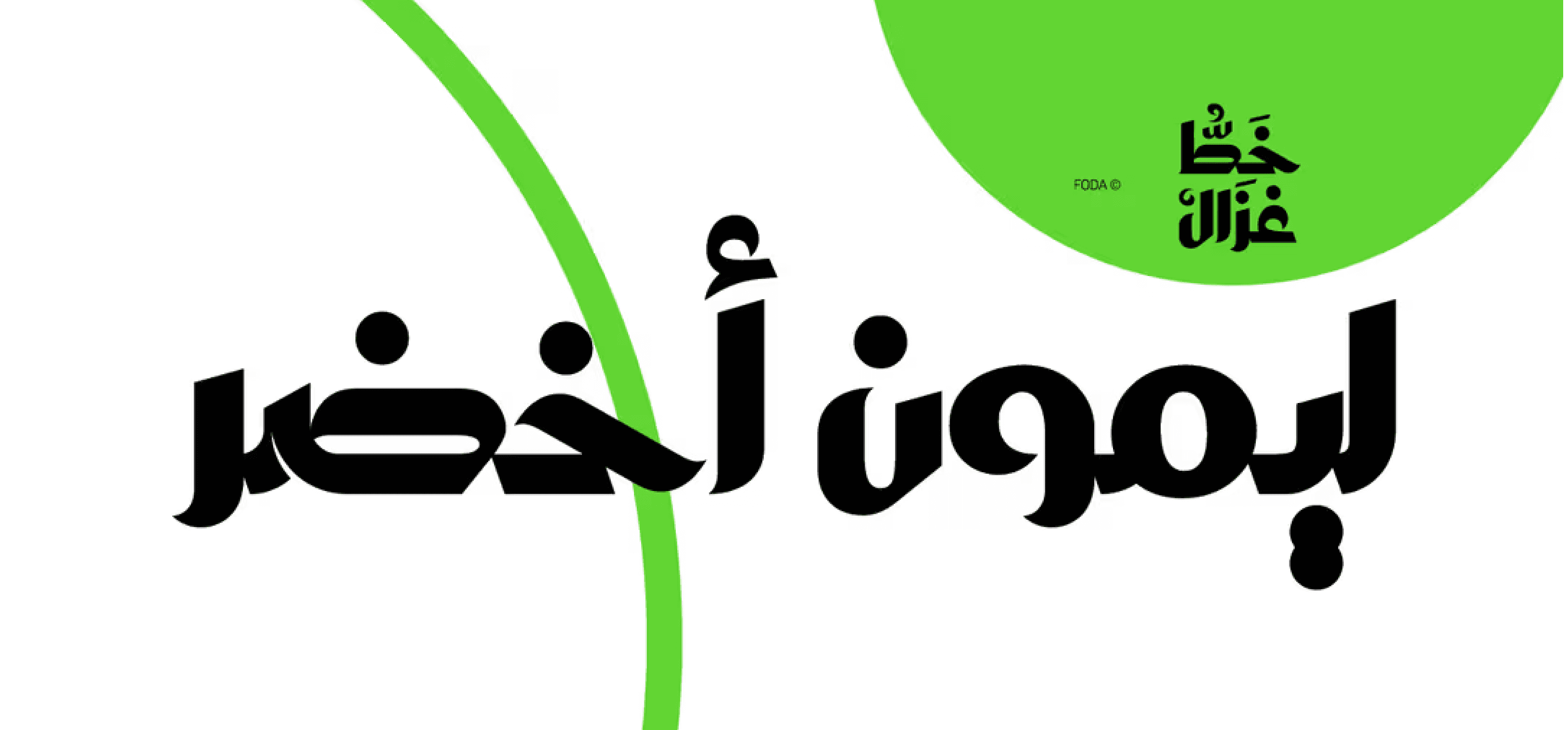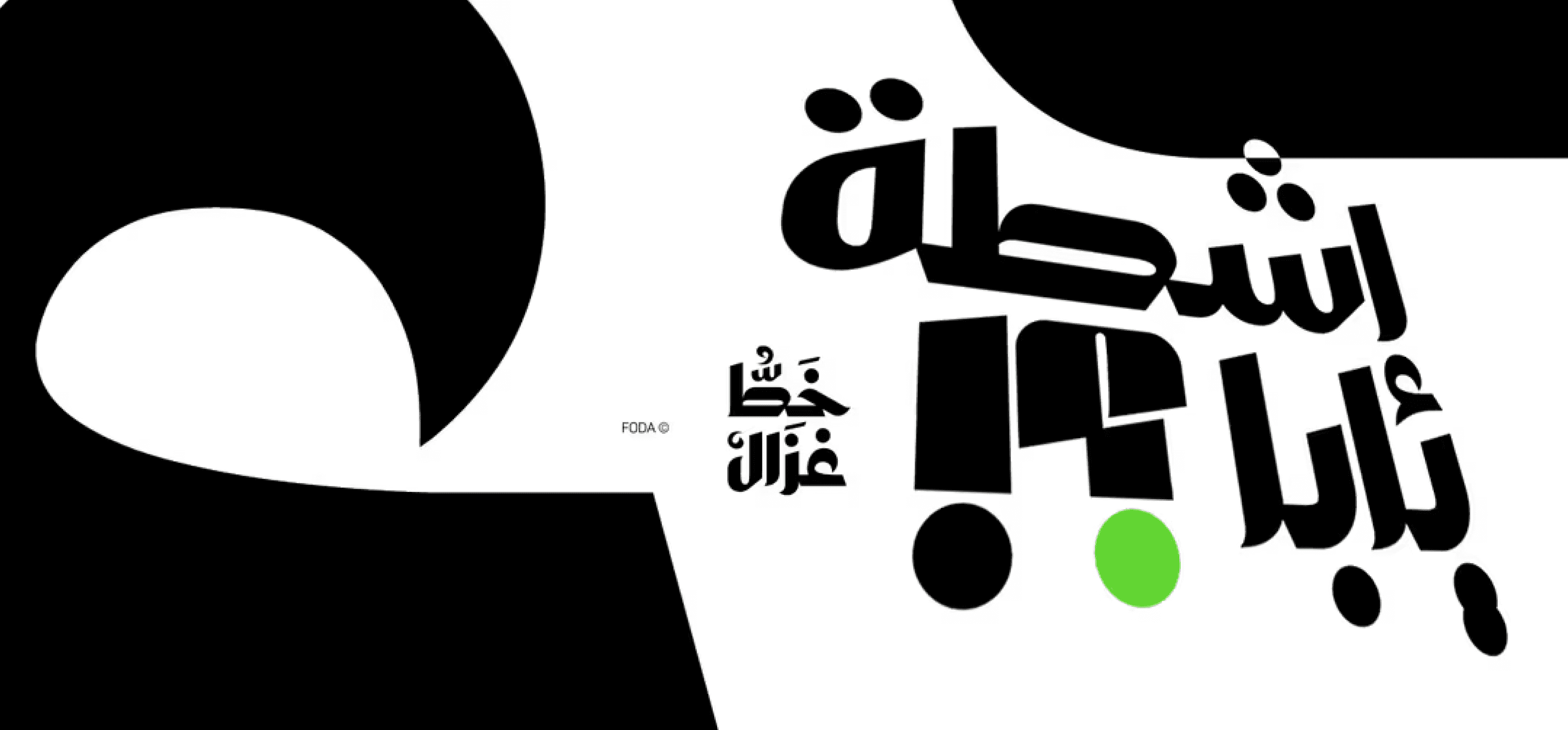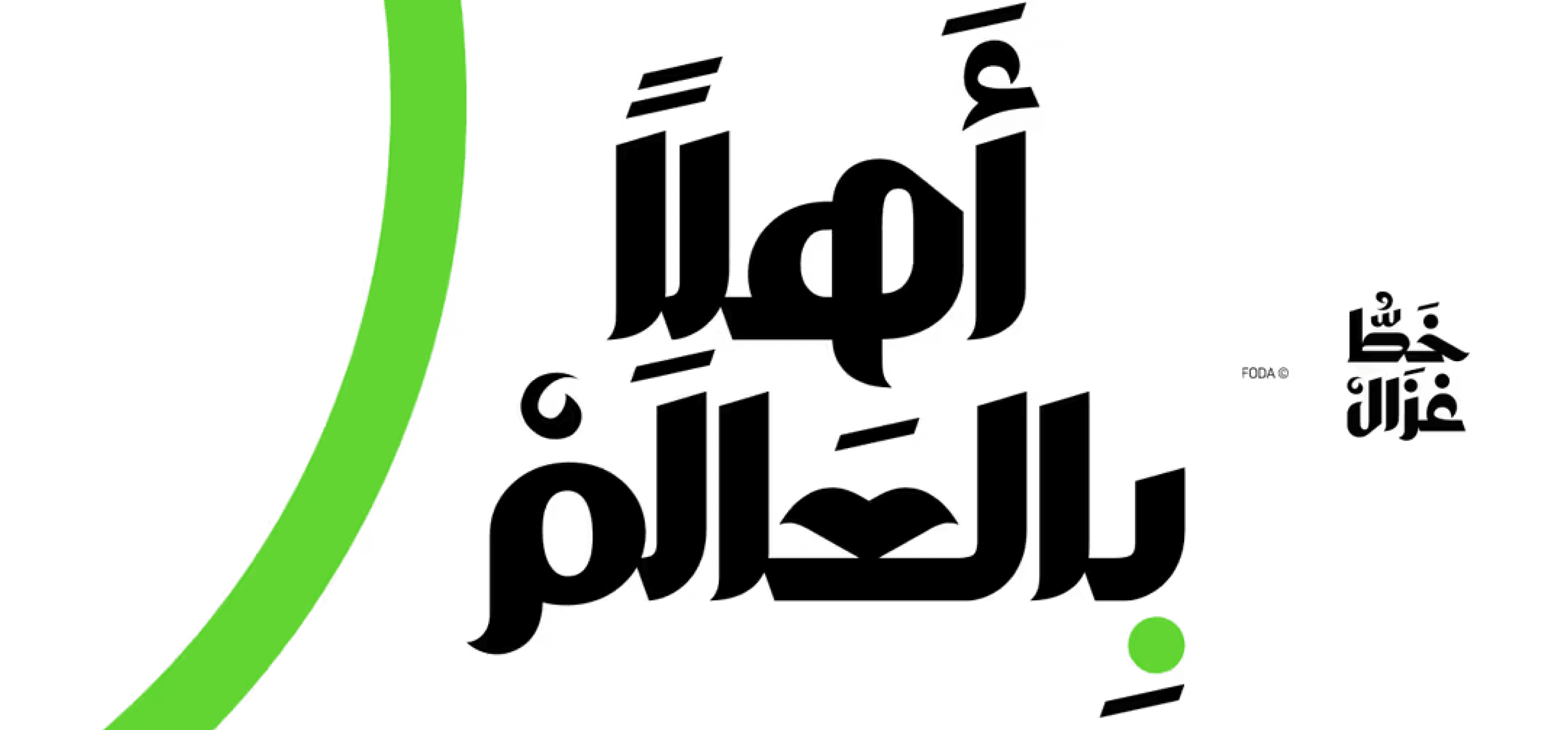
خط Ghazal هو خط عرض عربي بتباين عالٍ، يُستخدم بشكل رئيسي في العناوين، ويتوفر بوزن واحد فقط.
يُعتبر هذا الخط خيارًا ممتازًا لجميع أنواع المشاريع الإبداعية مثل الهوية البصرية والإعلانات.